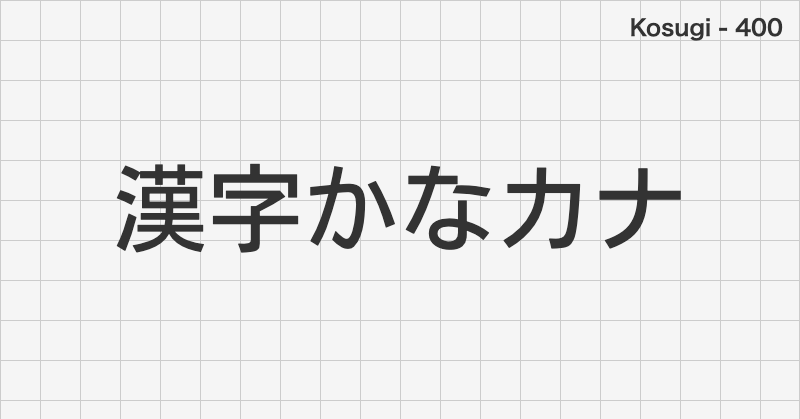
Kosugi – 商用利用できるゴシック体フリーフォント
Kosugi は、低いストロークコントラストとモノスペースのメトリクスを持つゴシック体フォントで、直線的なデザインが特徴です。美しさと可読性を追求したデザインです。
日本語、ラテン文字、ラテン文字拡張、キリル文字 に対応しており、国際化を前提としたデザインや文章表示に使えます。
Kosugi は、MOTOYA によって開発され、1950年代のデザインに基づいています。特に、日本の杉の木をイメージしたデザインが印象的です。
作者名 MOTOYA